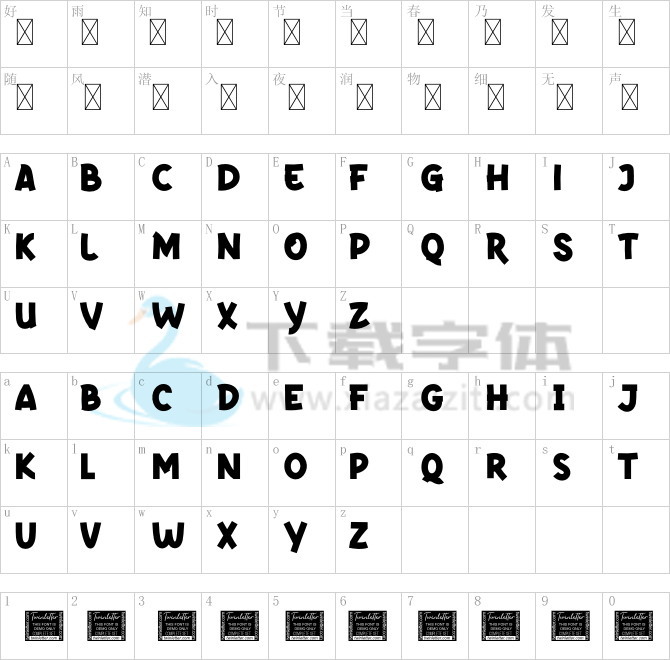
Aquatic Personal Use.otf字体下载,这款字体结构工整、笔画清晰,兼顾美观与易读性,适用于标题、正文、海报、包装、LOGO 等多种场景。字形优雅稳定,风格百搭耐看,适配日常排版与创意设计,让文字呈现更舒适、更具质感。Aquatic Personal Use.otf字体下载一笔一画,皆是细节,以均衡的比例、流畅的线条打造舒适视觉体验,字形端正大气,风格简约现代。无论是商业设计、品牌宣传还是日常排版,都能轻松驾驭,让文字更有格调与力量。Aquatic Personal Use.otf字体下载字体下载。